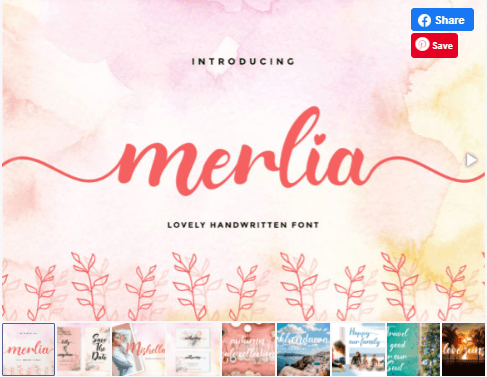
Merlia Font
Merlia - это плавный рукописный шрифт, описанный в элегантном стиле, идеально подходящий для ваших любимых проектов. Влюбитесь в его невероятно неповторимый и неподвластный времени стиль и используйте его для создания впечатляющих дизайнов!